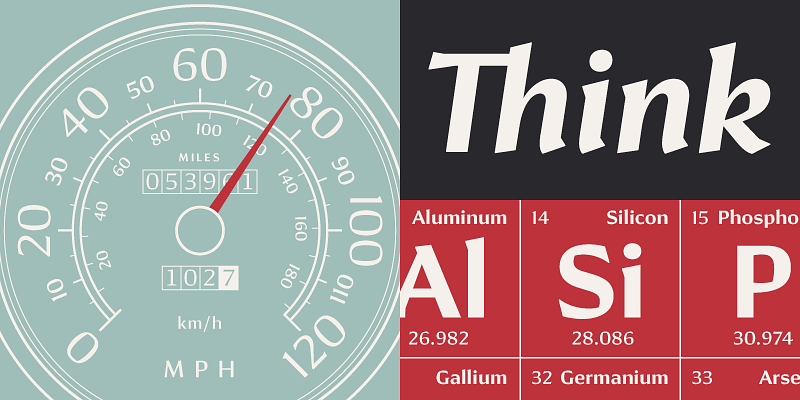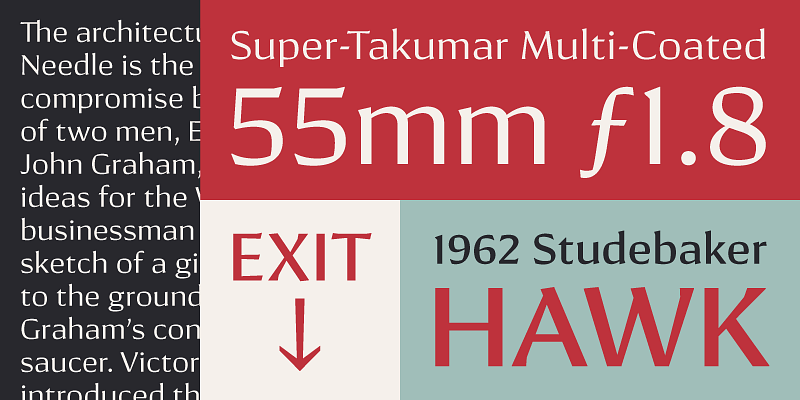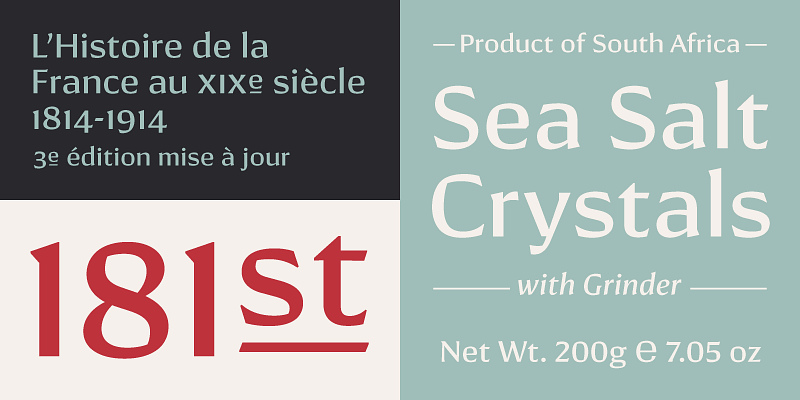
Conglomerate è una miscela unica di tratti tipografici sans e serif che si traducono in una famiglia di font pulita e versatile, con contatori ampi e aperti per la leggibilità del testo ma dettagli nitidi per le dimensioni dello schermo.